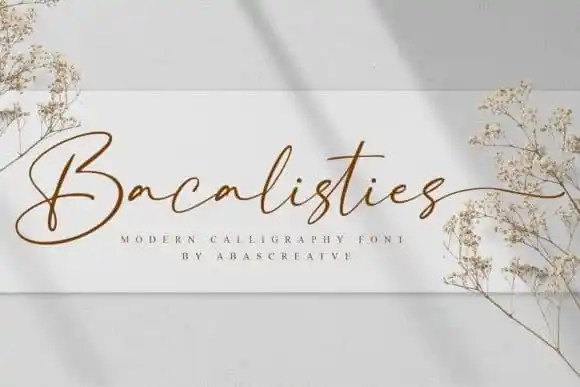
Bacalisties Script é uma fonte de script escrita à mão, com um estilo elegante e natural, criada por AbasCreative na plataforma 99designs. Esta tipografia captura a essência de uma caneta gel, resultando num design que transmite suavidade e elegância. Bacalisties está perfeitamente adaptado para criar um toque pessoal em cartões de convite de casamento, cards de agradecimento, mensagens, cartões de cumprimentos, logotipos e cartões de negócios. O formato variável da linha proporciona uma experiência visual única e incrível. Suas formas delicadas e alternativas chamativas oferecem um conjunto completo para qualquer tipo de projeto que precise de uma mão escritora. Este é o ideal para designers buscando incorporar um toque pessoal e elegante em suas criações visuais, seja em projetos de cartão ou logotipo.